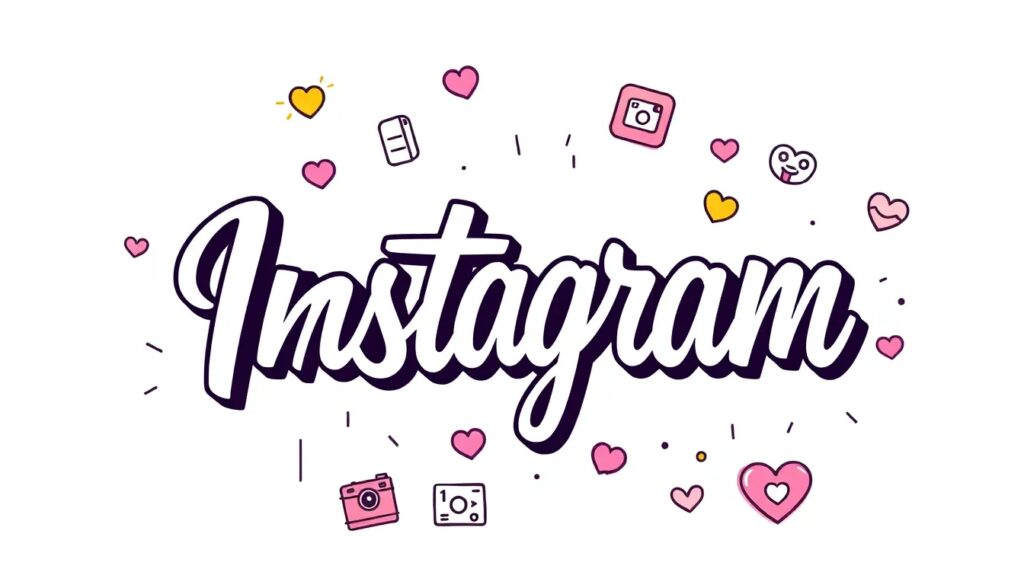
Cool fonts for instagram: los mejores estilos para copiar y pegar
Las redes sociales son una plataforma donde la estética y la originalidad juegan un papel fundamental. Las fuentes cool para Instagram se han convertido en una herramienta esencial para quienes desean destacar en esta red social. A través de ellas, los usuarios pueden personalizar sus biografías y publicaciones, dándoles un toque único.
En este artículo, exploraremos las diferentes maneras en que puedes utilizar un generador de fuentes para Instagram y por qué deberías optar por estas fuentes estilizadas en tu perfil.
¿Qué son las fuentes de Instagram?
Las fuentes de Instagram son estilos de texto que permiten a los usuarios personalizar sus publicaciones y biografías. Estas fuentes no son tipografías convencionales, sino que se generan a través de caracteres Unicode, que son representaciones gráficas de texto.
La variedad de estilos disponibles es impresionante, desde fuentes cursivas hasta decorativas. Utilizar cool fonts for Instagram puede ayudarte a resaltar tu perfil y hacer que tu contenido sea más atractivo visualmente.
- Fuentes cursivas
- Fuentes decorativas
- Fuentes modernas
- Fuentes artísticas
Con estas opciones, los usuarios pueden expresar su personalidad y mejorar la estética de su cuenta de Instagram.
¿Cómo funciona un generador de fuentes para Instagram?
Un generador de fuentes para Instagram es una herramienta en línea que permite transformar texto normal en diferentes estilos de fuentes. Funciona utilizando caracteres Unicode que son compatibles con la plataforma. Para utilizarlo, simplemente debes seguir estos pasos:
- Ingresa el texto que deseas transformar.
- Selecciona el estilo de fuente que más te guste.
- Copia el texto estilizado y pégalo en tu perfil de Instagram.
Estos generadores son muy fáciles de usar y no requieren habilidades técnicas avanzadas. Además, ofrecen una amplia variedad de estilos para elegir, lo que permite a los usuarios experimentar y encontrar la fuente perfecta para sus necesidades.
¿Cuáles son los mejores estilos de fuentes para copiar y pegar?
Los estilos de fuentes que elijas pueden variar según tu personalidad y el tipo de contenido que publiques. Algunas de las cool fonts for Instagram más populares incluyen:
- Fuentes en negrita: ideales para títulos y encabezados.
- Fuentes cursivas: perfectas para citas o énfasis.
- Fuentes decorativas: para un toque más artístico.
- Fuentes de escritura a mano: que añaden un toque personal.
Elegir el estilo adecuado puede ayudarte a transmitir el mensaje correcto y atraer la atención de tus seguidores. Recuerda que menos es más; no sobrecargues tus publicaciones con demasiados estilos diferentes.
¿Dónde puedo encontrar cool fonts for Instagram?
Existen numerosas herramientas en línea que te permiten generar cool fonts for Instagram. Algunas de las más recomendadas son:
- Font Generator: una herramienta simple y efectiva.
- IGFonts: ideal para generar fuentes específicas para Instagram.
- Cool Symbol: ofrece no solo fuentes, sino también símbolos creativos.
Estas plataformas son fáciles de usar y te brindan múltiples opciones para personalizar tu contenido. Además, algunas de ellas también ofrecen la posibilidad de crear símbolos para Instagram, lo que puede enriquecer aún más tus publicaciones.
¿Por qué deberías usar fuentes estilosas en tu perfil de Instagram?
Utilizar cool fonts for Instagram es una estrategia efectiva para hacer que tu perfil destaque. Los beneficios incluyen:
- Aumentar la visibilidad: un perfil atractivo puede captar la atención de más usuarios.
- Mejorar la estética: las fuentes estilizadas añaden un toque visualmente agradable.
- Reflejar tu personalidad: el estilo de fuente que elijas puede representar quién eres y tus intereses.
El uso de fuentes estilizadas puede influir positivamente en la interacción con tus seguidores, ya que un perfil bien diseñado invita a más personas a seguirte y participar en tus publicaciones.
¿Qué diferencias existen entre las fuentes decorativas y las fuentes estándar en Instagram?
Las fuentes decorativas son aquellas que añaden un elemento artístico y visualmente atractivo a tu contenido. Por otro lado, las fuentes estándar suelen ser más simples y fáciles de leer. Las diferencias clave incluyen:
- Estilo: las fuentes decorativas son más creativas, mientras que las estándar son más formales.
- Legibilidad: las fuentes estándar son generalmente más fáciles de leer en pantallas pequeñas.
- Uso: las fuentes decorativas son ideales para títulos y publicaciones visuales; las estándar son mejores para textos informativos.
Es importante saber cuándo usar cada tipo de fuente. Un equilibrio entre fuentes decorativas y estándar puede ayudar a mantener la claridad de tu contenido mientras añades un toque visual.
Ideas creativas para usar cool fonts for Instagram
Hay muchas maneras de incorporar cool fonts for Instagram en tu perfil. Aquí algunas ideas creativas:
- Utiliza fuentes estilizadas en tu biografía para captar la atención.
- Agrega citas inspiradoras con fuentes elegantes en tus publicaciones.
- Crea títulos llamativos para tus historias destacadas.
Experimenta con diferentes combinaciones de estilos para encontrar lo que mejor se adapte a tu marca personal. Recuerda que el objetivo es crear un perfil que refleje tu personalidad y atraiga a tus seguidores.
En conclusión, las cool fonts for Instagram son una excelente manera de personalizar tu perfil y mejorar tu interacción con otros usuarios. Asegúrate de elegir la fuente adecuada para cada publicación y experimenta con diferentes estilos para ver cuál resuena más con tu audiencia.